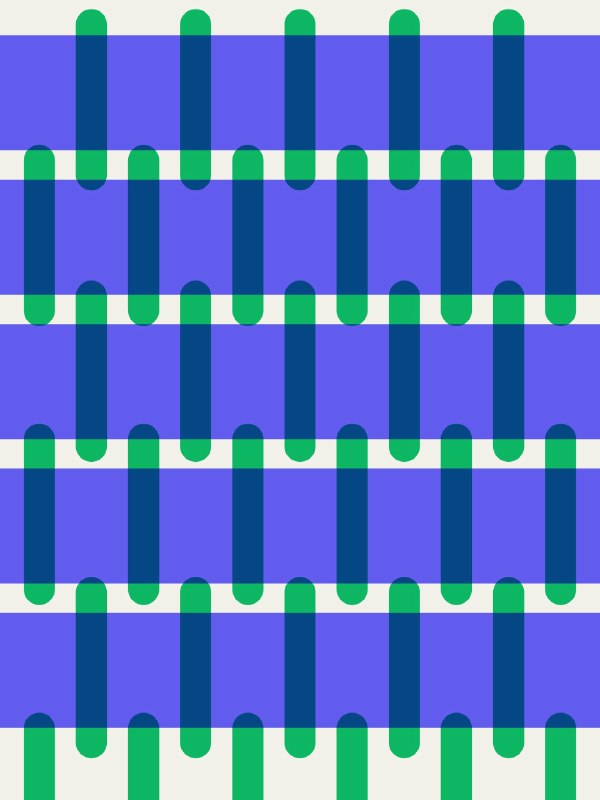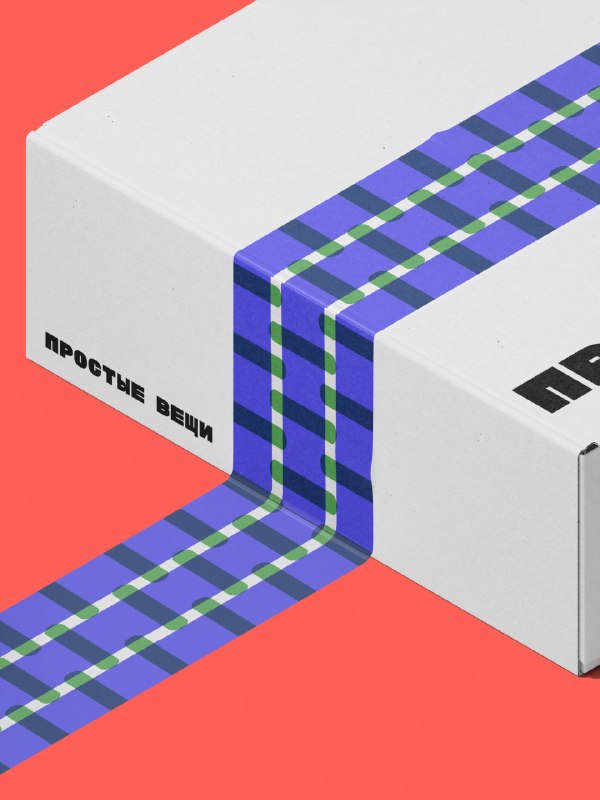
Новая айдентика для инклюзивных мастерских «Простые вещи». Часть II. Константы.
Когда появилась формулировка про равные возможности, сразу пришла идея использовать моноширинный шрифт, где у каждой буквы буквально равное пространство и равные возможности для проявления себя. CoFo Drifter просто сразу идеально лег, потому что в наборе попадаются всякие странности и особенности. Он работает в сочетании с простой графикой (тоже со сбивками), иллюстрациями мастеров Простых вещей и слегка сюрреалистичными аишками.
Шрифт
CoFo Drifter от Contrast Foundry